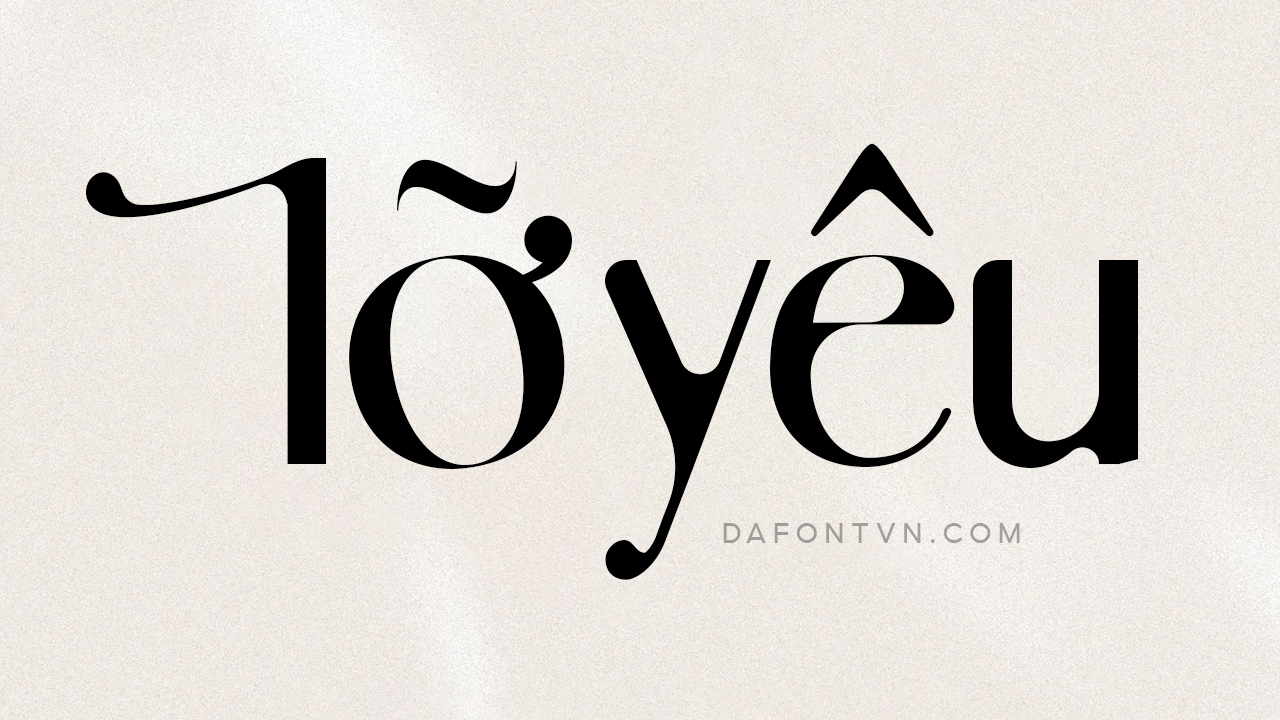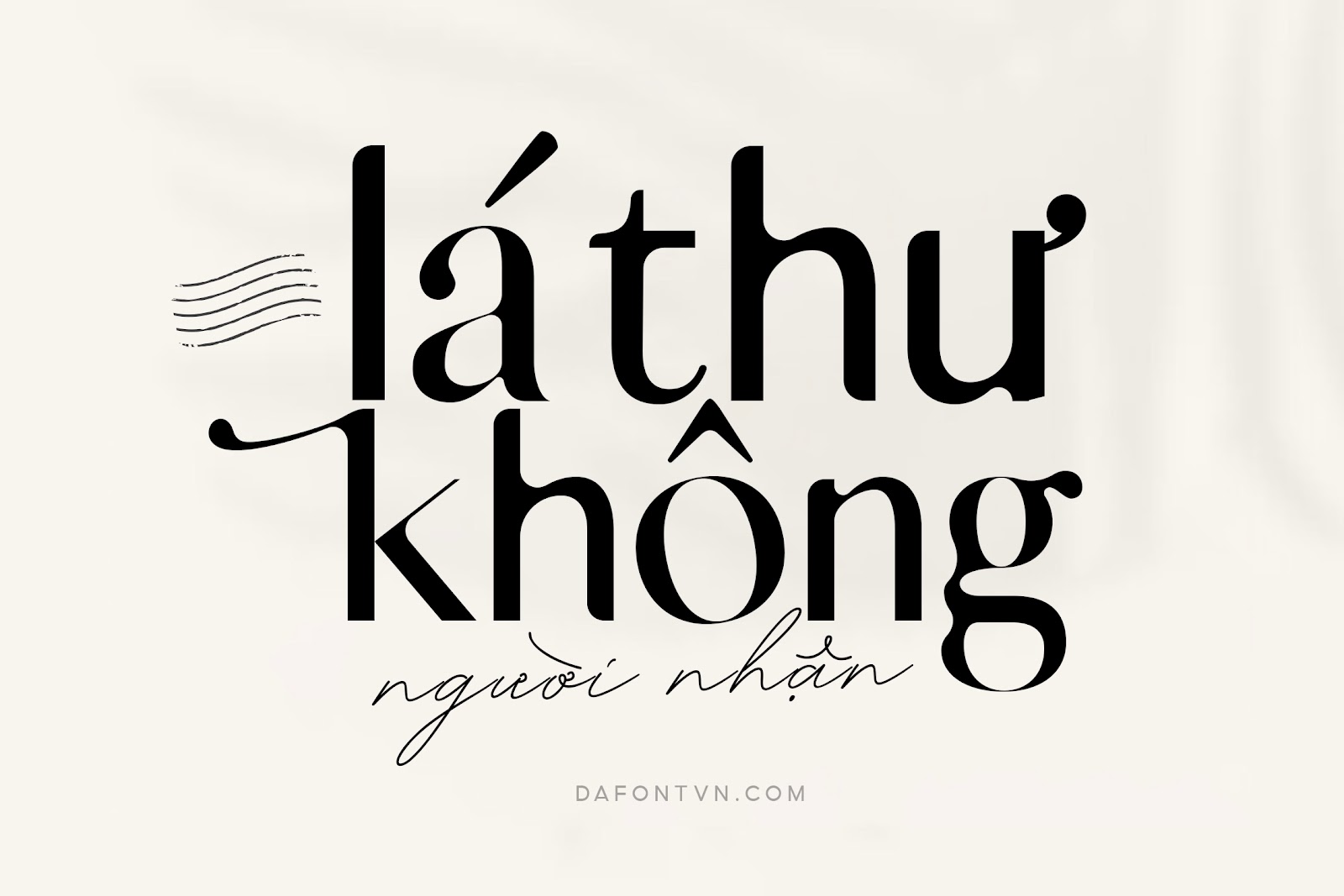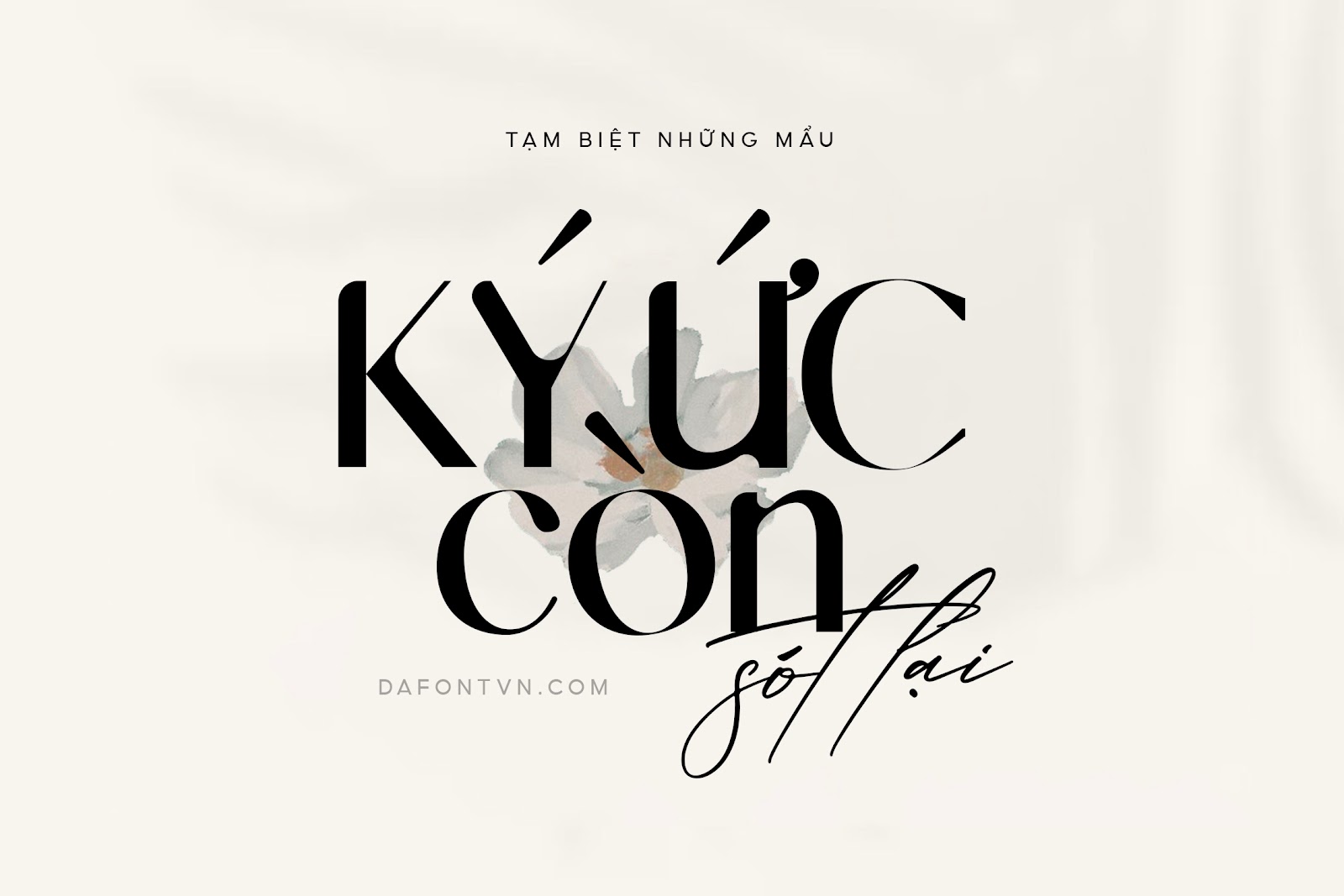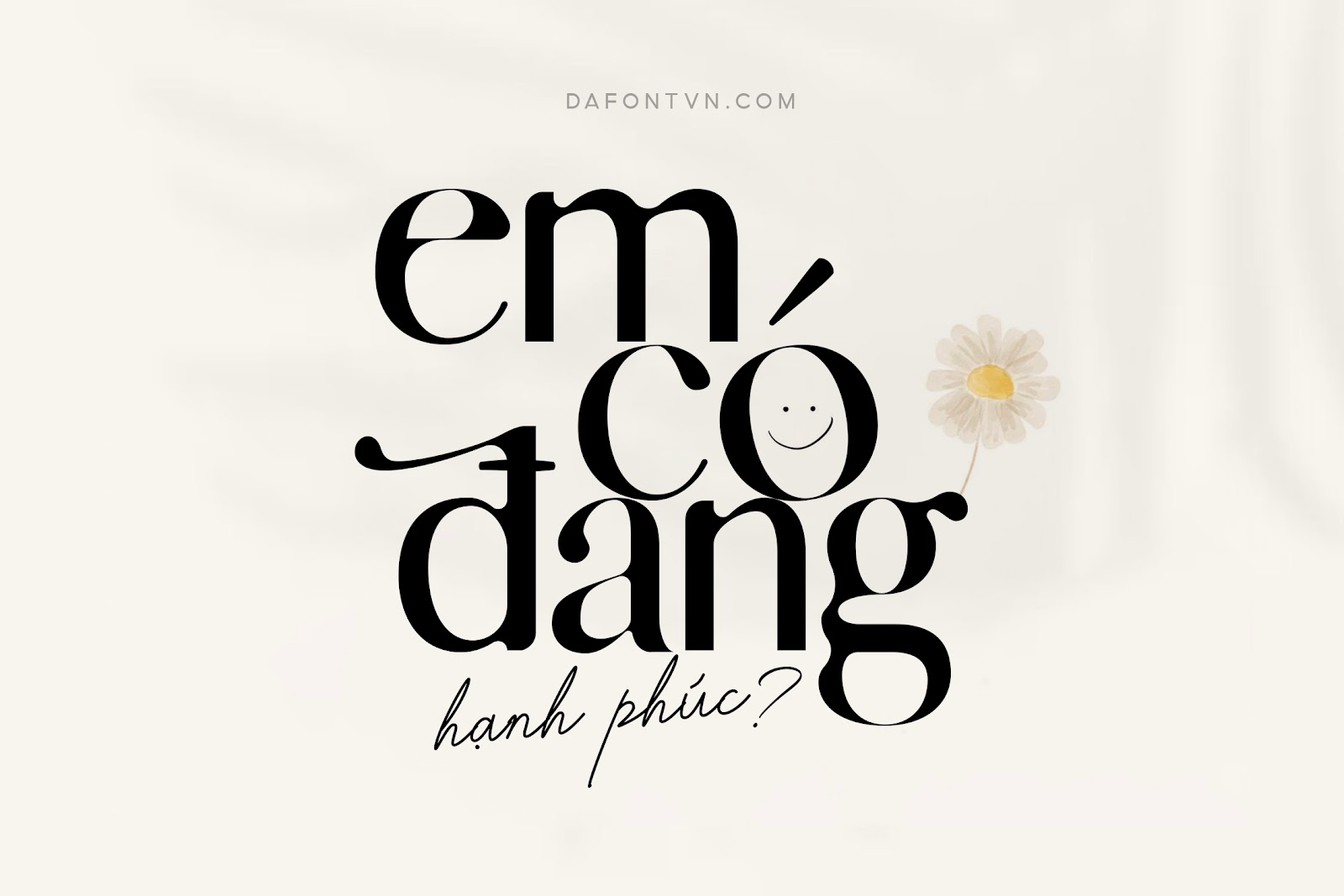
Font skylar việt hóa – 1 chiếc font xinh xắn
Giới thiệu 1 chiếc font xinh xắn skylar – modern ligature sans font
skylar là một kiểu font sans serif hiện đại và độc đáo với các nét chữ được thiết kế bo tròn mềm mại, đẹp mắt đem đến một cảm giác ấn tượng cho nhiều thiết kế của bạn. Ngoài ra phông chữ hiện đại này với 122 chữ ghép và các chữ thay thế vì vậy skylar phù hợp cho nhiều dự án như thiết kế logo, typography, thời trang, tạp chí, banner, poster… Để font chữ hiển thị tốt nhất bạn nên sử dụng font này làm điểm nhấn ở kích thước lớn.
Font skylar việt hóa đầy đủ, kerning, chỉnh sửa lại 1 số dấu cho phù hợp hơn với dấu tiếng Việt, ngoài ra font được mã hóa PUA để bạn sử dụng dễ dàng trên bất kỳ phần mềm nào.